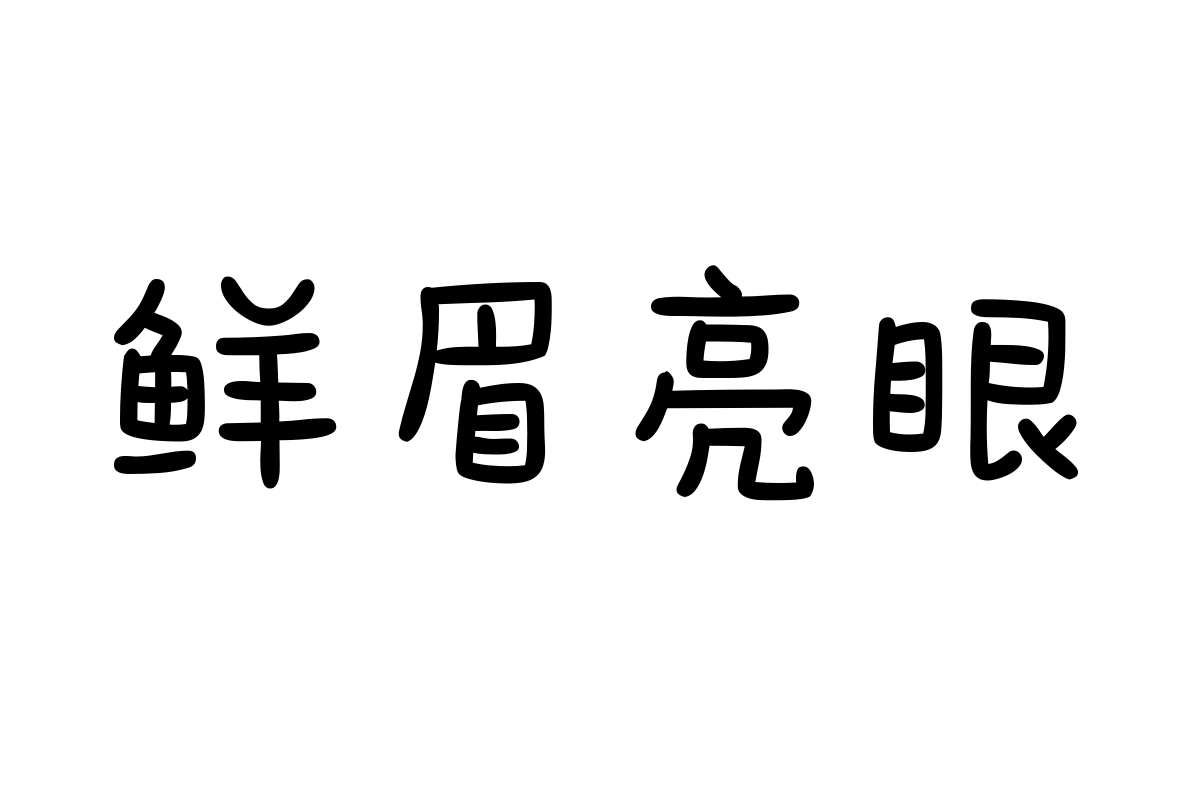
字体管家元气满满体是一款具有现代感和活力的中文字体,它的特点是笔画流畅、字形饱满且富有弹性。这种字体适合用于需要表达积极、健康、向上氛围的场合,如儿童用品、健身器材、运动品牌等。同时,它也适用于设计一些需要传达快乐、轻松氛围的图形元素,如插画、卡通形象等。
元气满满体的笔画粗细适中,既有力度又不失柔美,这使得它在视觉上给人一种轻松愉快的感觉。同时,这种字体的字形饱满,给人以力量感,使得整体设计更加有活力和动感。此外,元气满满体还具有一定的可读性,无论是在印刷还是电子屏幕上都能保持良好的视觉效果。
总的来说,字体管家元气满满体是一款非常适合用于需要传达积极、健康、向上氛围的设计元素的字体。